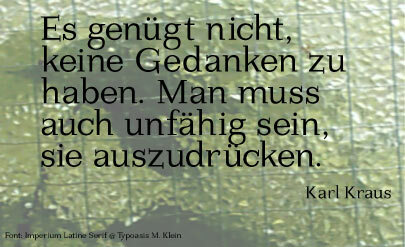
ImperiumSerif
Imperium Serif autorstwa Manfreda Kleina to darmowy krój szeryfowy, który wnosi spokojną, klasyczną elegancję, nie sprawiając przy tym wrażenia przestarzałego czy sztywnego. Mocne pionowe kreski i wyraźne, kwadratowe szeryfy dbają o stabilność i czytelność akapitów, a zaokrąglone kształty dodają odpowiedniej miękkości, zapobiegając zbyt technicznemu wyglądowi. Odstępy są przemyślane, dzięki czemu bloki tekstu czyta się płynnie zarówno na ekranie, jak i w druku.
Imperium Serif to spójny głos, który sprawdzi się zarówno w nagłówkach, jak i w tekście głównym, co ułatwia pracę przy projektach redakcyjnych, raportach czy minimalistycznych portfolio. Ten darmowy font świetnie odnajduje się w składzie książek, na blogach literackich, w przemyślanym brandingu i na wyrafinowanych plakatach, gdzie liczy się klarowność. Aby uzyskać czystą, współczesną kompozycję, spróbuj zestawić Imperium Serif w tekście głównym z lekkim bezszeryfowym krojem geometrycznym w podpisach lub nawigacji.